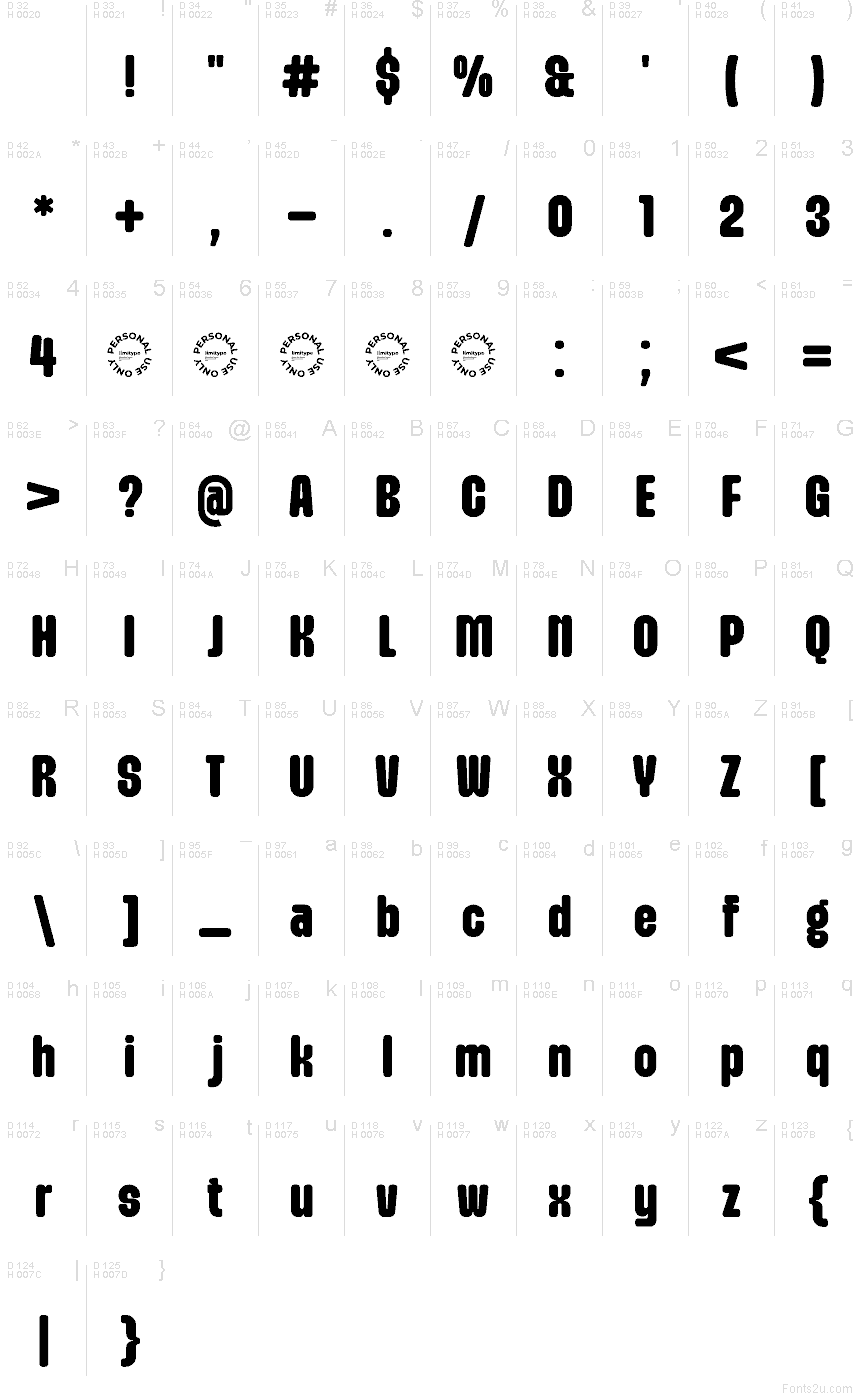
Smigle de Limitype es una tipografía gratuita, gruesa y redondeada, con esquinas suaves, formas compactas y un aire alegre, casi juguetón. Sus trazos anchos y su espaciado compacto aportan un carácter cercano y contundente, mientras que sus formas sencillas mantienen un estilo directo y sin complicaciones.
Esta fuente gratuita es perfecta para marcas informales, envases de snacks, pósteres infantiles, carteles de eventos y gráficos para redes sociales. También funciona muy bien en titulares cortos y tarjetas de presentación, donde sus siluetas robustas y su ritmo ajustado le otorgan una gran carga visual.